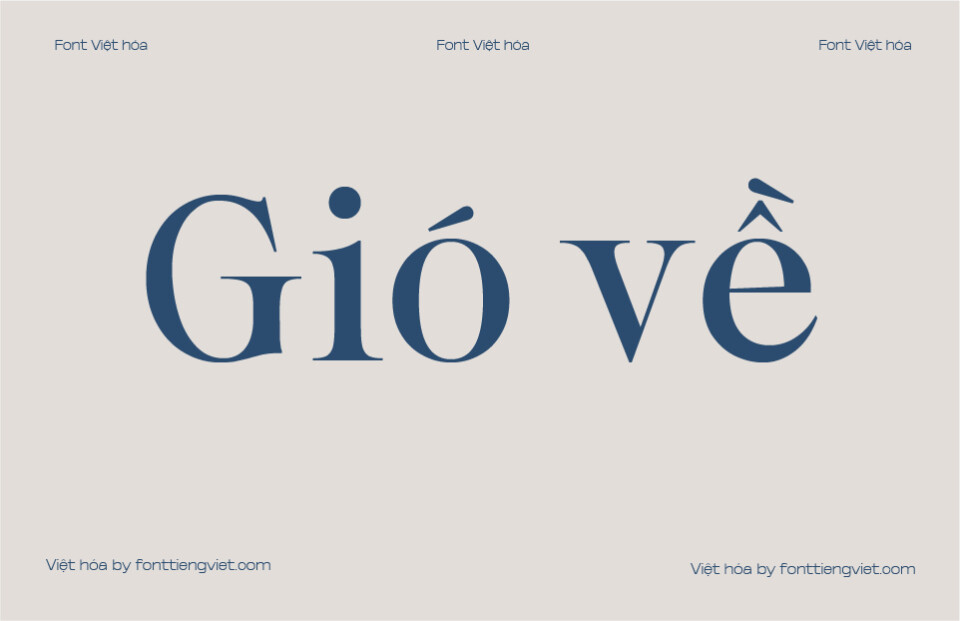
Font Việt hóa 1FTV VIP Hollywood Secrets Serif
Giới thiệu về Font Việt hóa 1FTV VIP Hollywood Secrets Serif
Trong thế giới thiết kế đồ họa hiện đại, việc lựa chọn một bộ Font Miễn Phí chất lượng luôn là ưu tiên hàng đầu của các nhà sáng tạo. Một trong những cái tên đang gây chú ý gần đây chính là Font Việt hóa 1FTV VIP Hollywood Secrets Serif. Đây là một bộ phông chữ thuộc phong cách Serif (có chân) mang đậm hơi thở của sự quý phái, quyền lực và không kém phần bí ẩn. Đúng như tên gọi “Hollywood Secrets”, bộ font này gợi nhắc đến những ánh đèn sân khấu lung linh, những tấm thảm đỏ danh giá và những câu chuyện điện ảnh đầy lôi cuốn. Việc sở hữu phiên bản Việt hóa giúp người dùng tại Việt Nam dễ dàng ứng dụng vào các dự án thiết kế tiếng Việt mà không lo lỗi dấu hay khoảng cách ký tự không đều.
Đặc điểm nổi bật của Font Việt hóa 1FTV VIP Hollywood Secrets Serif
Thiết kế tinh tế và đẳng cấp
Điểm thu hút nhất của Font Việt hóa 1FTV VIP Hollywood Secrets Serif nằm ở đường nét thanh mảnh kết hợp với những nét nhấn dày dặn, tạo nên sự tương phản mạnh mẽ nhưng vẫn vô cùng hài hòa. Các chân chữ được gọt giũa sắc sảo, mang lại cảm giác chuyên nghiệp và tin cậy. Đây là lựa chọn hoàn hảo cho các tiêu đề tạp chí thời trang, bìa sách nghệ thuật hoặc các ấn phẩm quảng cáo cho nhãn hàng cao cấp. Từng ký tự trong bộ font này đều được chăm chút kỹ lưỡng để đảm bảo tính thẩm mỹ cao nhất trên cả màn hình kỹ thuật số lẫn bản in truyền thống.
Khả năng hiển thị và tính đa dụng
Dù mang phong cách sang trọng, nhưng bộ font này vẫn giữ được độ đọc tốt ở nhiều kích cỡ khác nhau. Bạn có thể sử dụng nó cho các đoạn văn bản ngắn hoặc làm điểm nhấn cho các câu trích dẫn quan trọng. Đặc biệt, bộ font đã được tối ưu hóa các ký tự tiếng Việt, giúp các dấu thanh như huyền, sắc, hỏi, ngã, nặng được đặt ở vị trí cân đối, không làm mất đi vẻ đẹp nguyên bản của thiết kế. Điều này cực kỳ quan trọng đối với các bạn học sinh, sinh viên khi làm báo cáo thuyết trình hoặc các giáo viên khi thiết kế bài giảng điện tử sinh động.
Ứng dụng thực tế của bộ font trong đời sống
Thiết kế thương hiệu và marketing
Trong kinh doanh, việc tạo dựng hình ảnh thương hiệu uy tín là rất cần thiết. Sử dụng Font Việt hóa 1FTV VIP Hollywood Secrets Serif cho logo, danh thiếp hay menu nhà hàng sẽ ngay lập tức nâng tầm giá trị dịch vụ. Nó tạo ra một không gian nghệ thuật tinh tế, giúp khách hàng cảm nhận được sự chu đáo và đẳng cấp của doanh nghiệp. Ngoài ra, trong các chiến dịch marketing trên mạng xã hội, bộ font này sẽ giúp các bài đăng của bạn nổi bật hơn hẳn so với các phông chữ không chân phổ thông, thu hút sự chú ý của người xem ngay từ cái nhìn đầu tiên.
Sáng tạo trong giáo dục và học tập
Đối với môi trường học đường, các bạn học sinh có thể dùng bộ font này để trang trí tập san, làm thiệp chúc mừng thầy cô hoặc thiết kế các trang bìa tiểu luận. Nó giúp bài làm của các em trông chuyên nghiệp và có gu thẩm mỹ hơn. Các thầy cô giáo cũng có thể ứng dụng bộ font vào các slide bài giảng về lịch sử, nghệ thuật hay văn học để tạo không khí phù hợp với nội dung truyền tải, giúp học sinh hứng thú hơn với bài học. Sự kết hợp giữa truyền thống và hiện đại trong bộ font này chính là cầu nối tuyệt vời cho mọi ý tưởng sáng tạo.
Kết luận về bộ phông chữ Hollywood
Việc sử dụng Font Việt hóa 1FTV VIP Hollywood Secrets Serif không chỉ đơn thuần là chọn một kiểu chữ, mà là cách bạn thổi hồn vào tác phẩm của mình. Với sự sang trọng và tinh tế vốn có, bộ font này chắc chắn sẽ là công cụ đắc lực giúp bạn hiện thực hóa những ý tưởng bay bổng nhất. Hy vọng bài viết này đã cung cấp cho bạn những thông tin hữu ích về một lựa chọn Font Miễn Phí, Font Việt Hóa, Font Việt hóa 1FTV VIP Hollywood Secrets Serif tuyệt vời. Hãy thử trải nghiệm ngay hôm nay để thấy sự khác biệt trong từng đường nét thiết kế của mình!